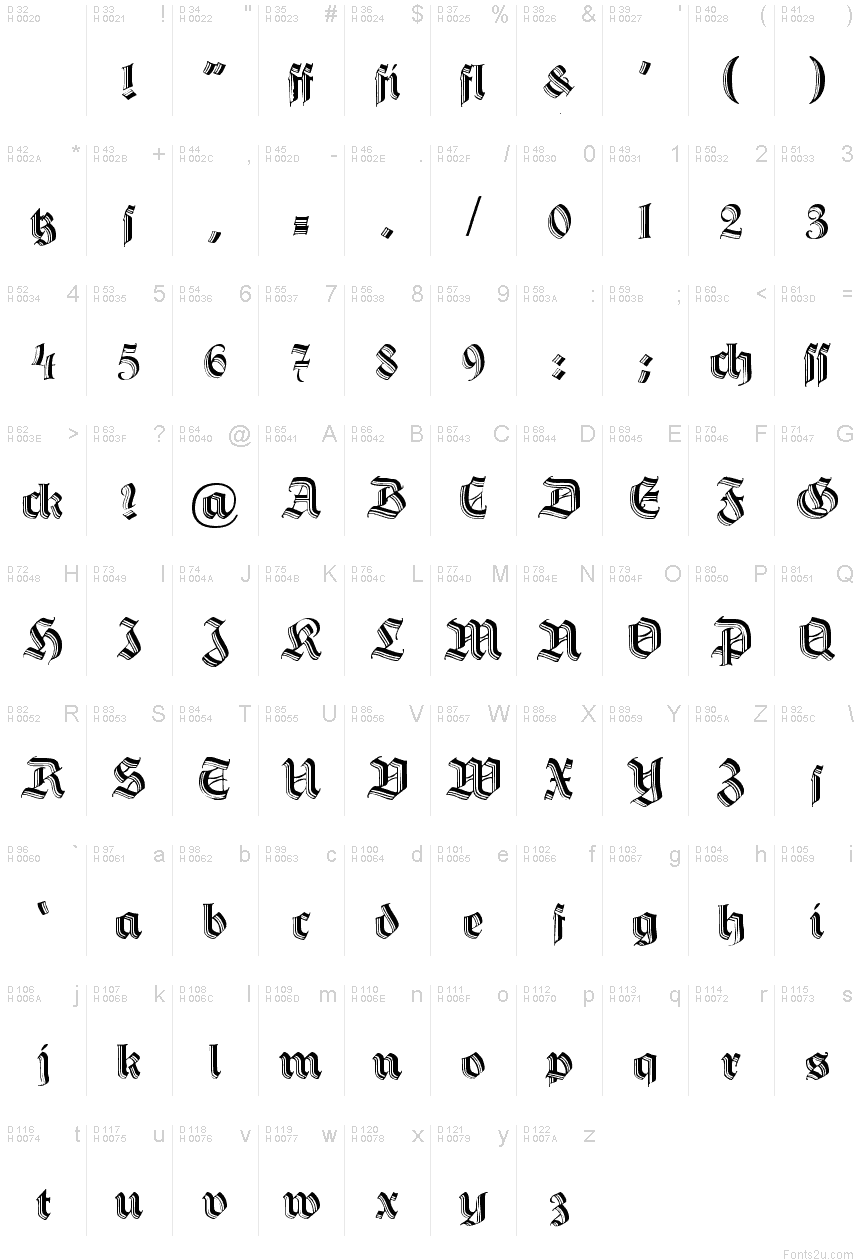
Hermann-Gotisch von Dieter Steffmann (Typographer Mediengestaltung) ist eine kostenlose mittelalterliche Gothic-Schrift, die die Wucht und Dramatik alter Blackletter-Manuskripte einfängt. Dicke, tintenschwarze Striche und scharfe, spornartige Kurven verleihen jedem Wort eine zeremonielle, fast liturgische Ausstrahlung, während der dichte, texturierte Rhythmus wirkt, als stamme er direkt von einer verwitterten Pergamentseite. Eine starke, dekorative Wahl, wenn Ihre Typografie historisch, feierlich und unverwechselbar altweltlich wirken soll.
Mit Hermann-Gotisch gewinnen Ihre Titel sofort jene kathedralenartige Gravitas, die auf Fantasy-Buchcovern, historischen Plakaten, LARP- und Cosplay-Brandings, Bandlogos, Veranstaltungseinladungen und thematischen Verpackungen glänzt. Dieser kostenlose Font wirkt am besten als Überschrift, groß gesetzt mit großzügigem Zeilenabstand, damit die dichten Formen atmen können. Kombinieren Sie ihn im Fließtext mit einer schlichten, modernen serifenlosen Schrift, um die Lesbarkeit Ihrer Layouts zu erhalten und gleichzeitig die gotischen Lettern in den Mittelpunkt zu rücken.